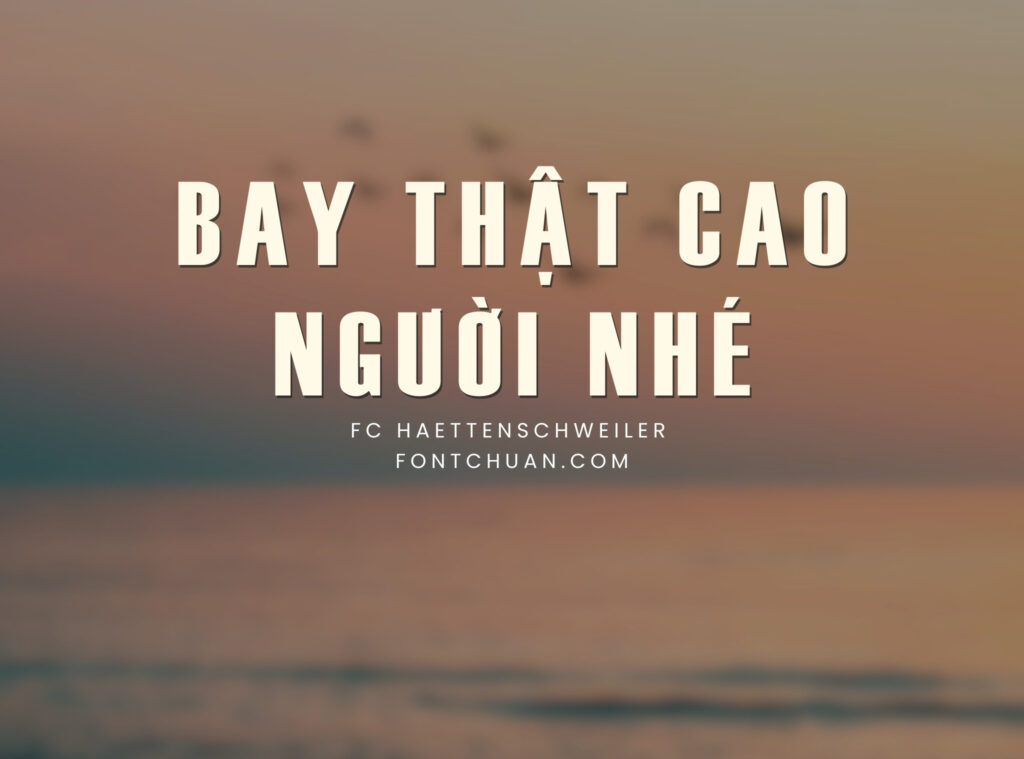
Haettenschweiler là một kiểu chữ sans-serif đậm và cô đọng, được biết đến với sự hiện diện mạnh mẽ và tác động thị giác cao. Phông chữ này có khoảng cách giữa các chữ cái chặt chẽ, tạo nên một diện mạo mạnh mẽ và nổi bật.
Khác với Font Haettenschweiler việt hóa của những team khác thường có phí, Font FC Haettenschweiler là một phiên bản Việt hóa siêu chất lượng mà lại miễn phí từ nhóm Font Chuẩn, tinh chỉnh hoàn hảo, hỗ trợ đầy đủ các ký tự tiếng Việt, giúp người dùng dễ dàng áp dụng trong các dự án sáng tạo.
Với thiết kế đậm nét và cô đọng, FC Haettenschweiler phù hợp cho các ứng dụng như tiêu đề, logo, thiết kế thương hiệu và các ấn phẩm in ấn. Trong lĩnh vực sự kiện, phông chữ này có thể được sử dụng trong các dịp như lễ hội, thiệp cưới và sinh nhật. Ngoài ra, FC Haettenschweiler cũng thích hợp cho các ngành nghề như làm logo, quảng cáo, giáo dục và công nghệ.
Đặc biệt, với phong cách mạnh mẽ và nổi bật, FC Haettenschweiler còn có thể được ứng dụng như một font chữ Trung Thu cho các poster, banner hoặc ấn phẩm quảng bá mùa lễ hội. Các đường nét đậm, dứt khoát sẽ tạo nên sự cuốn hút và làm nổi bật không khí sôi động của Trung Thu, phù hợp cho cả thiết kế truyền thống lẫn hiện đại.